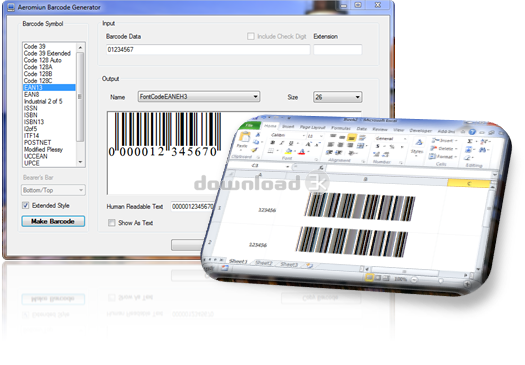
Aeromium Barcode Fonts 4.0
"Aeromium is a set of premium barcode fonts."
Aeromium Barcode Fonts es un conjunto de fuentes de código de barras de alta calidad, profesionales y premium para su organización. Cada una de las fuentes ha sido cuidadosamente desarrollada y diseñada para garantizar la máxima capacidad de lectura y lectura. Los códigos de barras admitidos se usan y adoptan comúnmente en muchas industrias. Todas las fuentes de código de barras han sido diseñadas para cumplir con estrictas especificaciones de la industria, incluidos los últimos requisitos de SUNRISE.Los siguientes formatos de fuentes de código de barras están disponibles en el paquete:
Junto con las fuentes de códigos de barras TrueType existentes, este paquete de software permite a los usuarios crear códigos de barras en muchas aplicaciones diferentes como Microsoft Excel, Microsoft Word, Wordpad, Crystal Reports, Adobe Photoshop, Adobe Illustrator y otros editores gráficos.
Este paquete de software se incluye con una aplicación auxiliar independiente que puede verificar los datos de entrada, generar dígitos de verificación y traducir los caracteres de entrada en caracteres de código de barras que cumplen con todos los estrictos requisitos de la industria de códigos de barras. Además, este paquete también viene con Visual Basic para Fórmulas de Aplicación (VBA) que permite flexibilidad para generar códigos de barras en Microsoft Excel y Crystal Reports. Este paquete incluye además un Kit de desarrollo de software (SDK) .Net para permitir a los desarrolladores integrar fácilmente la generación de códigos de barras en sus aplicaciones a medida.
Tipos de códigos de barras compatibles:
Código39
Código39 (ASCII extendido / completo)
Código 93
Codabar racional
Code128 Auto, Code128A, Code128B y Code128C
GS1 128 (UCC / EAN)
Industrial 2of5
Intercalado 2of5
ITF14
Numeración de artículo europeo 13 (EAN13)
Numeración de artículo europeo 8 (EAN8)
Plessy modificado (MSI)
Código de producto universal A (UPCA)
Código de producto universal E (UPCE)
Número de libro estándar internacional (ISBN)
Número estándar internacional del libro 13 (ISBN13)
Número de serie estándar internacional (ISSN)
Extensión 2 (EXT2) y Extensión 5 (EXT5)
Esta nueva versión incluye un fabricante de códigos de barras para generar imágenes de códigos de barras de calidad profesional.